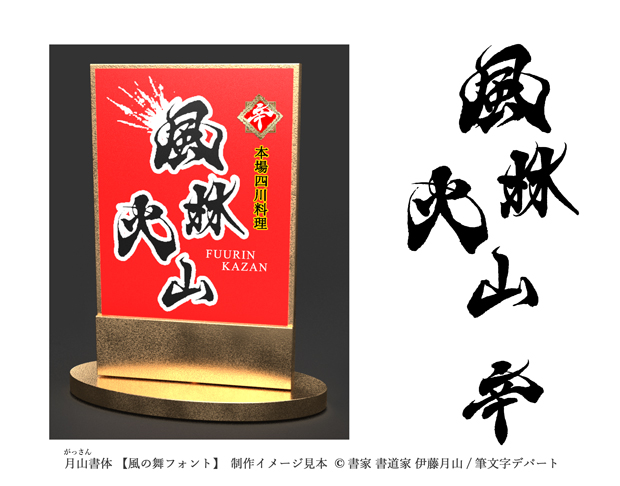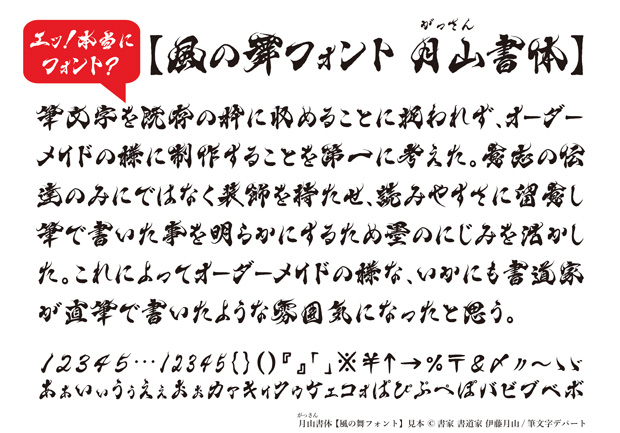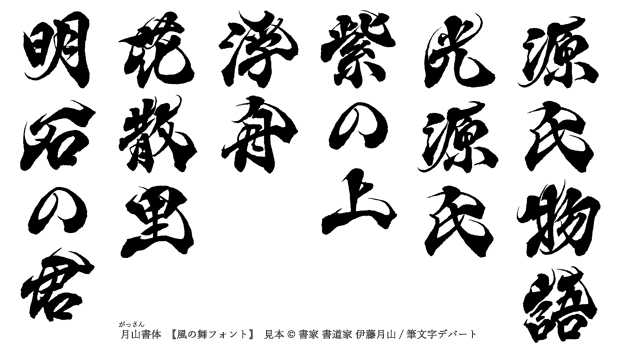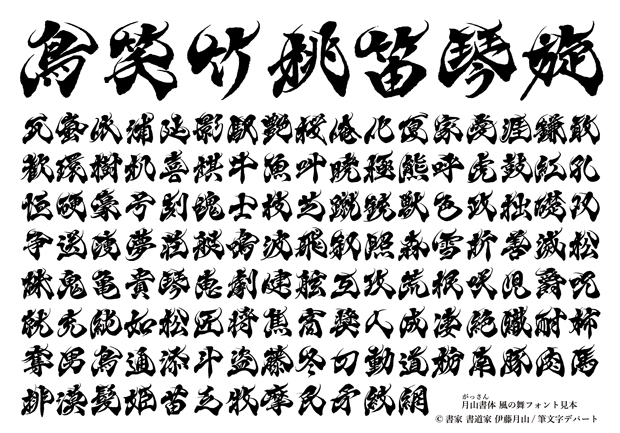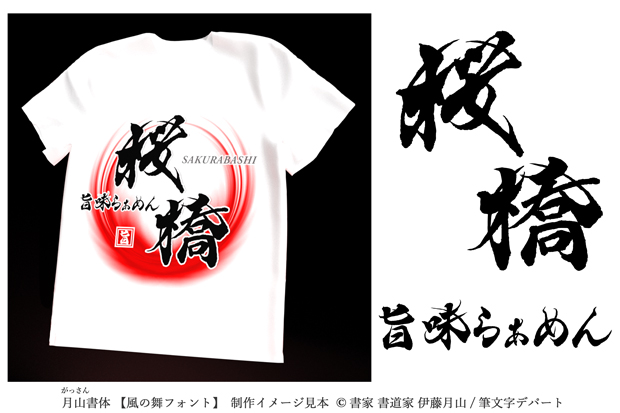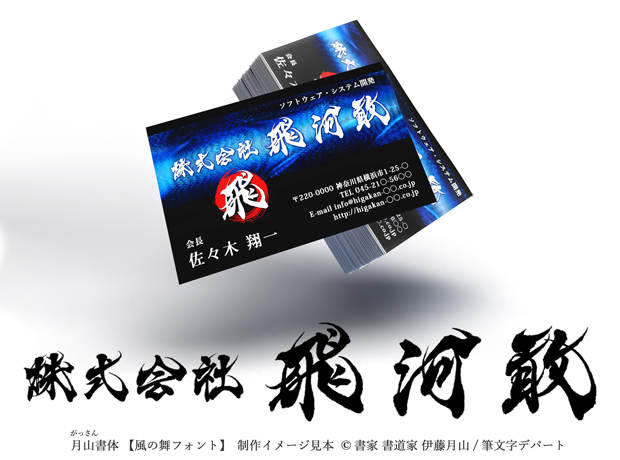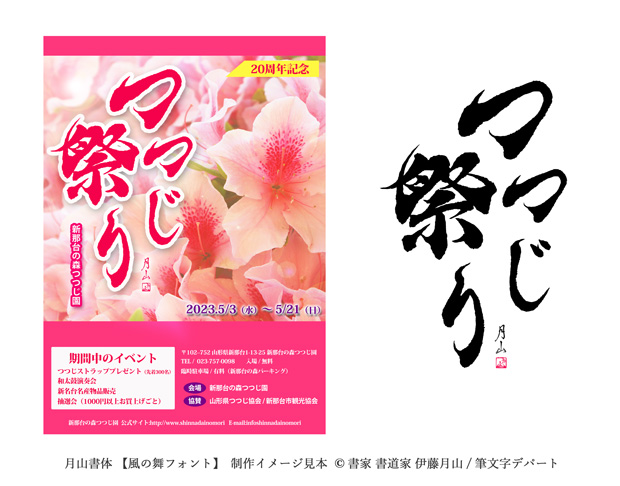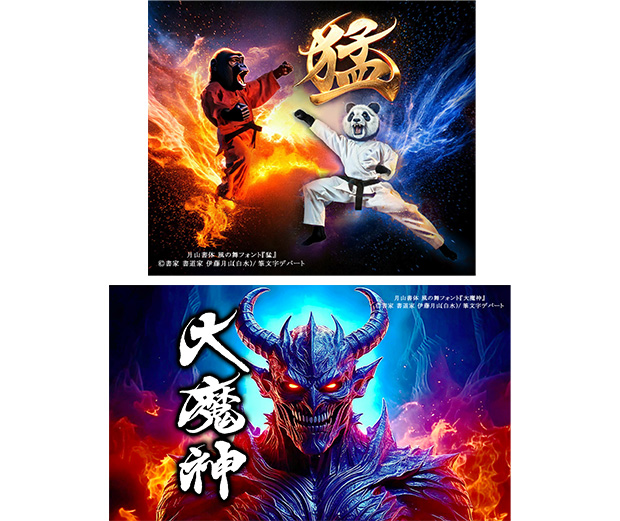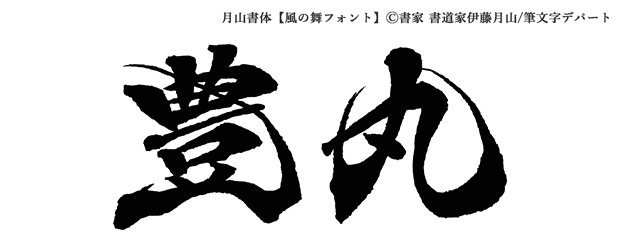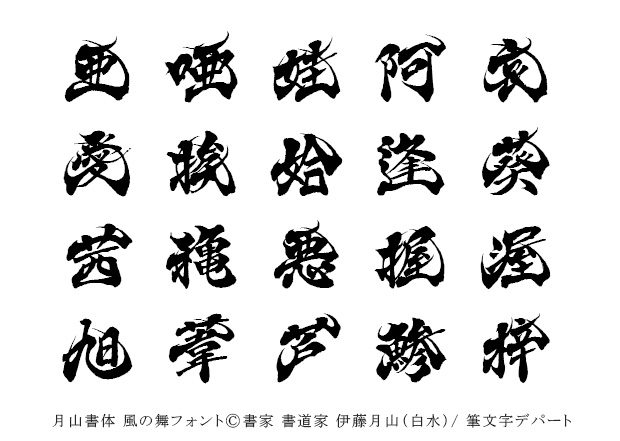
風の舞フォント(1文字)
【風の舞フォントの活用例】
※納品時には黒色の筆文字を送信いたしますが納品後はご購入者様が色の変更、縁取り、また立体感をつけていただくことが可能です。例えば、上記画像のゴリラVSパンダの激闘ゲームの演出文字【猛】のように立体感のある煌びやかな金色文字の周囲に火の粉を飛ばし、【大魔神】のように白文字の周囲を黒い影で縁取り、ゲームの世界観を深め存在感のある筆文字に仕上げています。
この毛筆フォント『風の舞』書体は「カッコいい・高級感・躍動・力強い・奇抜・太字・インパクト・美しく爽やか」という様に様々な要素を兼ね備えることが出来るように工夫して創作しました。
また文言によって個々の筆文字の大小・縦長・横長等の変化により筆文字としての完成度が上がると思っております。そのためフォントファイルそのものの販売はせず個別の文言の販売を致しております。ご注文の際はその都度、微調整して納品しております。
「風の舞フォント」は、書家/書道家 伊藤月山(白水)が考案した風舞書(ふうぶしょ)という商標登録済の書体を基に創作デザインした、風に舞っている姿の表現の毛筆フォントです。
全国規模の諸流派書道展では特に注目を浴び、一般的な筆文字よりも風の舞フォントの書体に感動する人が多くいらっしゃいました。さらに、名刺サイズのカードに一般的な筆文字と風の舞フォントの書体の両方を印刷し無料で提供した結果、ほとんどの方が風の舞フォントを選んでいただいたというデータもあります。
書き手の書家/書道家 伊藤月山(白水)はイタリア親善訪問全日本教育書道代表団団員として推薦された実力があります。また、日本最大級の国際政治カンファレンスやNHKの大型ドキュメンタリー番組などのオーダーメイド制作にも多数携わっています。
アンカーポイント多く墨の滲みを具象化したフォントです。書道の息吹を感じることができます。
風の舞フォントの書体は書家/書道家 伊藤月山(白水)が独自に考案した構成法「風舞書®」を応用した、完全オリジナルの個性的な毛筆書体です。また漢字の偏(へん)や旁(つくり)の使い回しは一切せず1文字ずつ手書きで丁寧に書き上げました。
【風の舞フォント:桜橋 旨味らぁめん】
全国の人気ラーメンショップが集う野外ラーメンフェスタの会場でスタッフが着る白地Tシャツのイメージ画像です。冷凍ラーメンやインスタントラーメンでは決して再現できない外国人観光客にも人気の美味しい拉麺。自家製麺、独自の秘伝のスープ、手作りの具材等こだわり抜いた究極の味噌ラーメンを情熱的に作る店員の意気込みを赤丸の炎で表現した店舗ロゴのイメージです。
【風の舞フォント:つつじ祭り】
山形県の観光協会が協賛のつつじ祭りのポスターのイメージ画像です。美しい花々など華麗なイメージのお祭りやイベントにも風の舞フォントの書体は合います。お花祭りの他、よさこい祭り、ねぶた(ねぷた)祭り等のように高揚感溢れるお祭りから獅子舞やダンスに関連したものにもお薦めの書体です。
【風の舞フォント:株式会社 飛河敢】
ソフトウェア・システム開発会社のビジネス名刺印刷の作成イメージ画像です。風の舞フォントのデジタルデータ納品後は法人向け名刺の他、個人事業主や個人の趣味名刺等にもプリントしてご使用可能です。
【風の舞フォント:風林火山 辛】
高級中華料理(四川料理)店の屋外用防水スタンド看板のイメージ画像です。高級感があり辛くて美味しい料理を提供するお店の雰囲気が伝わるように、ゴールドと赤を基調とした看板とし、その中に力強く躍動する筆文字店舗ロゴが目立ちます。(風の舞フォントには見本の「風」のように墨滴を散らした素材は入っておりません。価格は別途お見積致します。)風の舞フォントは飲食店用の看板以外にも展示会での商品PRや商談会での壁面タペストリー等にも商用利用ができます。
【文章の見本】
風の舞フォントの説明を横書きの文章にした見本です。
【源氏物語・光源氏・紫の上・浮舟・花散里・明石の君】
源氏物語(作者:紫式部)の登場人物の名前で、漢字仮名交じりの縦組みの見本です。この見本のように、あなたのお名前を名刺にしてみてはいかがでしょうか。活字と違い力強く元気で躍動的な風の舞フォントは印象に残り、役に立つと思います。
【デザイン】
手書きの毛筆書体「風の舞フォント」は、私(書家/書道家 伊藤月山(白水)が考案した風舞書(ふうぶしょ)という商標登録済の書体を基に創作デザインした、風に舞っている姿の表現の毛筆フォントです。そして漢字は楷書体と隷書体、時に行書体等を取り入れてアレンジし日本の伝統的な書体と独自性を融合させた、フォントとしては異例の個性的なデザインを持った全く新しい書体です。
なお、風の動きは主に隷書体の横画を応用しています。
始筆は蚕の頭、終筆は燕の尾を表現する、いわゆる蚕頭燕尾と言われる隷書の最も特徴的な手法を取り入れています。このフォント作品の波磔に関して言えば、送筆が終わるといったん筆の動きを止め右斜め下に送筆し、進む方向に逆回転しながら円を描くようにはね上げています。これによってダイナミックな躍動感を生み出しています。また和風デザインを心がけ、書道にとって肝要となる墨のにじみを活かす為にフォント化する過程でアンカーポイントを豊富にしました。そして単純な線にならない様、太細のメリハリをつけることに留意しました。
また、風の舞フォントは1文字1文字がロゴになり得るように丁寧に創作しています。
その一方で、制作者の個性が現れます。つまり、可読性を重んじて個性的な文字を試みない明朝体やゴシック体等のフォントと風の舞フォントは相反しています。用途によって、どのフォントを使用するか使い分けることが大切だと思います。
風の舞フォントはできるだけ機械的要素を排除し、いかに個性を引き立たせるかに焦点を合わせて創作しました。私の毛筆フォントを「フォント文字ではないみたい。」「まるでオーダーメイドのように悠々としていてお洒落。」等々と評価してくれる方々がいらっしゃいますが、私のフォント文字をこの様におっしゃる方はどうやら購買欲が刺激されるようです。
方形に捉われつつも、伸び伸び感を表現するために章法の中で文字や文字の空間を大事にしました。
この風の舞フォントは、よさこい祭りのチーム衣装、県知事の書籍、劇団のグッズ、高校のクラブ旗、熊野古道同好会Tシャツ、社訓、鮨店、バスケットボールの応援旗、同人誌タイトルロゴなど企業様、個人様問わず多種多様の用途で幅広くご注文をいただいています。
風の舞フォントを使用対象物に使用することによって縁起の良い爽やかな風が舞い込み、ご購入者様や目に触れた人にとって特別な雰囲気を創り出すことを願っています。